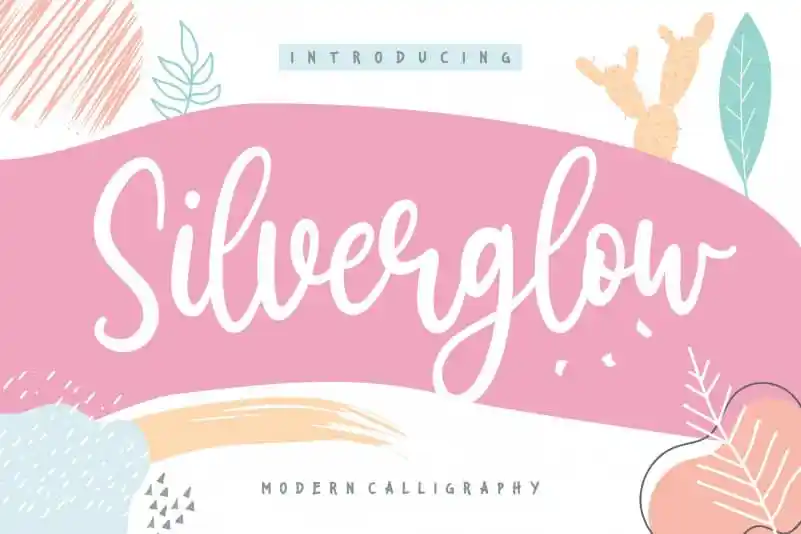
Silverglow Calligraphy Font – Download Grátis
Aproveite uma nova experiência com Silverglow Playful Modern Calligraphy Font, perfeita para designers que buscam algo especial para seus projetos editoriais. Embora seja uma fonte moderna e moderna, ela mantém um toque de elegância e graça na forma de letras, tornando-a um recurso valioso tanto para criações visuais formais quanto para aqueles desejosos de um toque mais leve em suas produções. Sua característica principal é a versatilidade da Silverglow Playful Modern Calligraphy Font. Ela oferece uma mistura única entre simplicidade e sofisticação, o que permite aos designers criar trabalhos que vão do elegante às vezes românticas até as criações mais ousadas e modernas. Com esta fonte, você pode explorar diferentes estilos, adaptá-la para vários ambientes de design, ou até mesmo adaptá-la para um projeto específico. Além disso, a Silverglow Playful Modern Calligraphy Font é ideal tanto para títulos quanto para o texto interno, proporcionando uma variedade de opções dependendo do contexto. Essa fonte moderna e divertida traz um toque único à sua produção editorial, tornando-a um verdadeiro recurso que pode fazer qualquer projeto brilhar ainda mais.